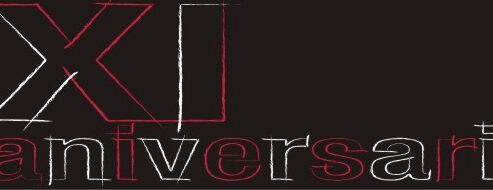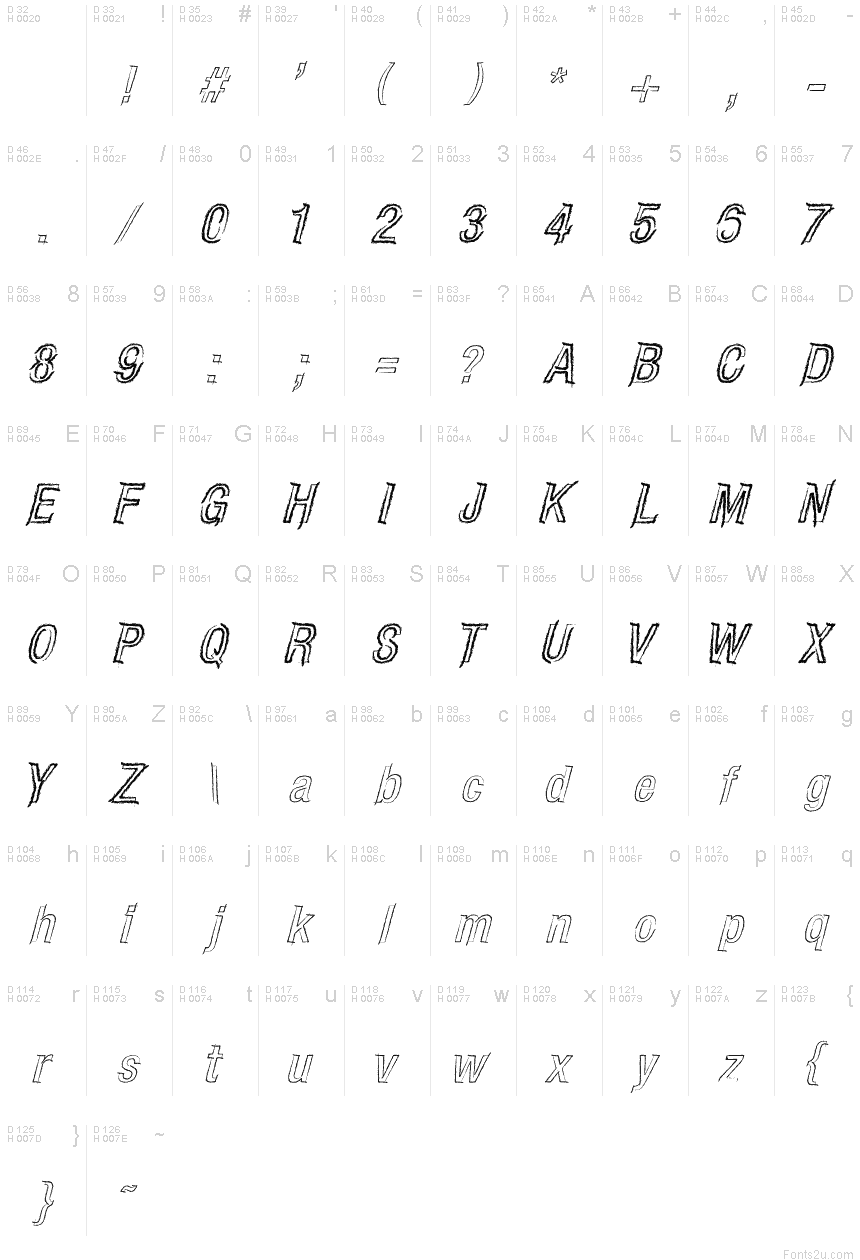
CARBONCILLO PALO Italic
Carboncillo Palo Italic autorstwa Manuela Lage to darmowy krój pisma typu display o węglowych konturach, charakteryzujący się niespokojnym pociągnięciem i poszarpanymi krawędziami suchego patyczka do rysowania. Jego pochylone litery posiadają podwójne kontury i nierówne zadrapania, tworząc surowy, ręcznie wykonany rytm zamiast schludnego, grawerowanego wykończenia.
Ten wytarty kontur nadaje tytułom plakatów i oprawie muzycznej natychmiastową, warsztatową energię, zachowując jednocześnie wystarczającą otwartość, by dobrze wyglądać na zdjęciach. Użyj tego darmowego fontu do identyfikacji wizualnych festiwali, okładek magazynów, grafik deskorolek czy ekologicznych opakowań, gdy projekt wymaga śladów węgla rysunkowego, które wyglądają, jakby zostały wrysowane bezpośrednio w kompozycję.